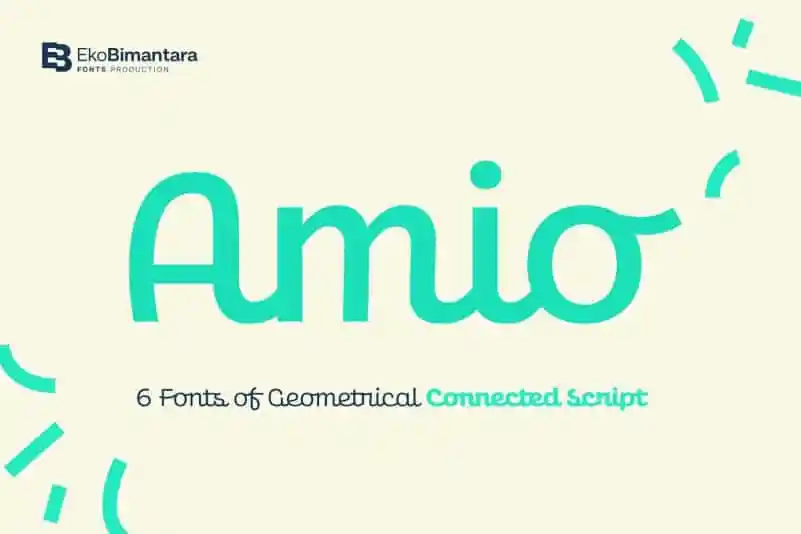
Amio Script Font – Download Grátis
A Amio Script Font é uma delicada seleção de linhas script que captura a essência dos desenhos humanizados. Seu visual alegre e descontraído torna-a perfeita para qualquer projeto criativo, seja ele um logo memorável ou uma identidade visual única. Com seu amplo espectro de seis estilos (de suave à extra-destemperada), essa fonte pode ser usada em diferentes ambientes – desde a capa de revista até o design de aplicativos e produtos digitais, oferecendo uma variedade de opções para atender aos seus objetivos. Combinadas perfeitamente, as Amio Script Fonts criam um design visual que chama atenção e é ideal para qualquer projeto em busca de um toque único e alegre.